לא כולם מבינים כיום עד כמה לפונטים יש משמעות והשפעה על חיינו בניהם, פונט תנכי עם ניקוד. הם מעבירים מסרים, מתקשרים בין הקורא למותג או למפרסם ומצליחים להשרות אווירה מעניינת ורגועה וזאת בהתאם כמובן לסיטואציה בה הפונט מוטמע.
התנ"ך, אבן היסוד של היהדות והנצרות, הוא לא רק אוסף של סיפורים עתיקים וחוכמת חיים, אלא גם יצירת אמנות לשונית ותרבותית. אחד ההיבטים המרתקים של יצירה זו הוא הפונטים הייחודיים שבהם נכתב התנ"ך לאורך הדורות.
לכן כולם רוצים לדעת על פונט תנכי עם ניקוד למגוון של מטרות כי מדובר בפונט הכי מרגש ומחבר לשורשים שקיים. אם גם אתם סקרנים בואו לגלות את כל מה שאתם צריכים.
פונט תנכי עם ניקוד – בדיוק מה שחיפשתם
פונטים תנ"כיים הם למעשה משפחת פונטים בעברית שפותחה במיוחד לכתיבת והדפסת התנ"ך. הם משמרים את הצורה והסגנון של הכתב העברי הקדום, ומעניקים לתנ"ך מראה אותנטי ומכובד.
פונטים אלה אינם רק כלי להעברת מידע, אלא גם סמל לרצף ההיסטורי והתרבותי של העם היהודי. השימוש בפונט שהינו פונט תנכי עם ניקוד אינו מוגבל רק לתנ"ך עצמו. הם משמשים גם בספרי קודש אחרים, כמו סידור, מחזורים והגדות של פסח.
הם מעטרים כתובות קיר בבתי כנסת, במוסדות דת ובבתים פרטיים ומופיעים ביצירות אמנות ופריטי יודאיקה.
מעצבים גרפיים רבים משלבים אותם בלוגואים, בכותרות ובפרסומים בעלי אופי יהודי ומעניקים להם אווירה של מסורת וקדושה וישנם גם אלו המעדיפים פונט כתב יד המביא לתחושה אישית יותר.
מהו כתב רש"י ואיך הוא מתאים לפרסומים?
כאשר מדובר על פונט תנכי עם ניקוד בין הפונטים התנ"כיים הבולטים ניתן למנות את כתב רש"י, כתב עתיק ומסוגנן ששימש בעיקר לפירושים לתנ"ך ולתלמוד. כתב זה בעל אותיות מוארכות ומעוגלות מעניק לטקסט מראה יוקרתי ומלכותי.
הוא מזוהה בעיקר עם פירוש רש"י, אחד הפרשנים החשובים ביותר של התנ"ך והתלמוד ומסמל את העמקות והחוכמה של הפרשנות היהודית המסורתית. פונט נוסף הוא כתב סתם, פונט פשוט וקריא ששימש להדפסת התנ"ך עצמו.
פונט זה על קוויו הישרים וצורותיו הברורות נועד להקל על הקריאה ולהנגיש את התנ"ך לקהל הרחב. הוא מייצג את הרצון להפיץ את דבר האל לכל שכבות העם, ולהפוך את התנ"ך לספר נגיש ומוכר לכל.
גופן קורן, פונט מודרני שפותח במיוחד להדפסת התנ"ך קורן הוא דוגמה לפונט תנ"כי שהצליח לשלב בין מסורת לחדשנות. הוא משלב אלמנטים של כתב רש"י וכתב סתם ויוצר פונט קריא ואלגנטי כאחד. גופן קורן הפך לפופולרי מאוד בשנים האחרונות והוא משמש כיום להדפסת מהדורות רבות של התנ"ך.
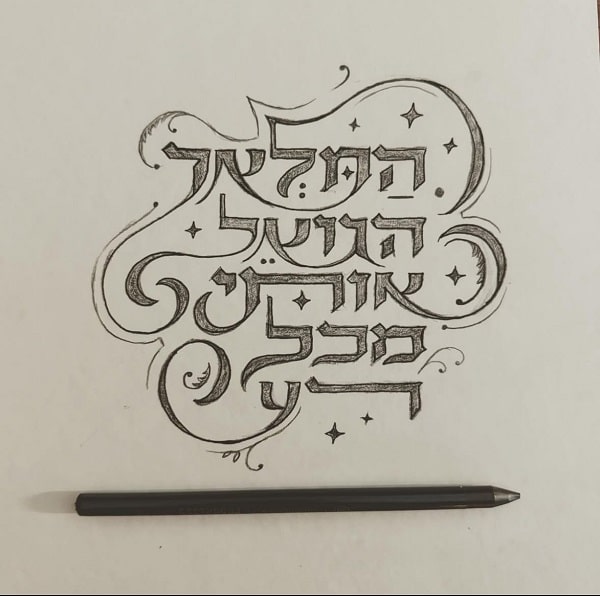
איך פונט תנכי מסתדר עם החדשנות והטכנולוגיה?
עם התפתחות הטכנולוגיה והחדשנות הפכו הפונטים התנ"כיים לנגישים יותר מתמיד וגם פונט תנכי עם ניקוד לקח חלק במהפכה זו. כיום ניתן למצוא אותם בקלות באינטרנט ולהשתמש בהם במחשב ובטלפון החכם. אתרים מקצועיים העוסקים בתחום זה מתמחים בפונטים עבריים ומציעים מגוון רחב של פונטים תנ"כיים באיכות גבוהה.
הנגישות של הפונטים התנ"כיים בעידן הדיגיטלי פתחה אפשרויות חדשות לשימוש בהם. מעצבים גרפיים יכולים לשלב אותם פונטים בעברית בקנבה ובפרויקטים דיגיטליים כמו אתרי אינטרנט, אפליקציות ומשחקים.
מורים יכולים להשתמש בהם ליצירת מצגות וחומרי לימוד אינטראקטיביים. ואנשים פרטיים יכולים להוסיף נופך של מסורת וקדושה למסמכים האישיים שלהם, כמו הזמנות לחתונה או בר מצווה, כרטיסי ברכה ואיגרות אישיות.
הפונטים התנ"כיים, ביניהם גם פונט תנכי עם ניקוד כמובן, הם הרבה יותר מסתם אותיות על דף. הם שומרים על מסורת עתיקת יומין, מעצבים את האופן שבו אנו תופסים את התנ"ך, ומאפשרים לנו להתחבר לטקסטים הקדושים ביותר שלנו בצורה אותנטית ומכובדת.
בעידן הדיגיטלי, הם ממשיכים להתפתח ולהשתלב ביצירות חדשות, ומבטיחים כי המורשת התרבותית היהודית תמשיך לחיות ולפרוח גם בדורות הבאים.
פונט תנכי עם ניקוד – שאלות נפוצות
האם כל ספרי התנ"ך מודפסים באותו הפונט?
לא. ישנם סוגים שונים של פונטים תנ"כיים וביניהם פונט תנכי עם ניקוד וכל הוצאה לאור בוחרת את הפונט המתאים לה ביותר בהתאם לקהל היעד ולסגנון המבוקש.
למשל ישנן הוצאות לאור מסורתיות שיכולות לבחור בפונטים עתיקים כמו כתב רש"י או כתב סתם בעוד שהוצאות לאור מודרניות עשויות לבחור בפונטים קריאים יותר כמו גופן קורן או פונטים דומים.
הבחירה בפונט משפיעה על מראה התנ"ך ועל האופן שבו הקורא תופס את הטקסט.
האם ניתן להוריד פונטים תנ"כיים בחינם?
כן, ישנם לא מעט אתרים המציעים הורדת פונטים מיוחדים בעברית ללא עלות וחשוב לבחון היטב את האתרים מהם אתם מורידים את הפונטים.
בדקו את איכות הפונטים, בדקו את המוניטין של האתר וודאו שהחברה שממנה אתם מורידים את הפונטים על מנת שבאמת תקבלו פונטים איכותיים מספיק לצרכים שלכם.